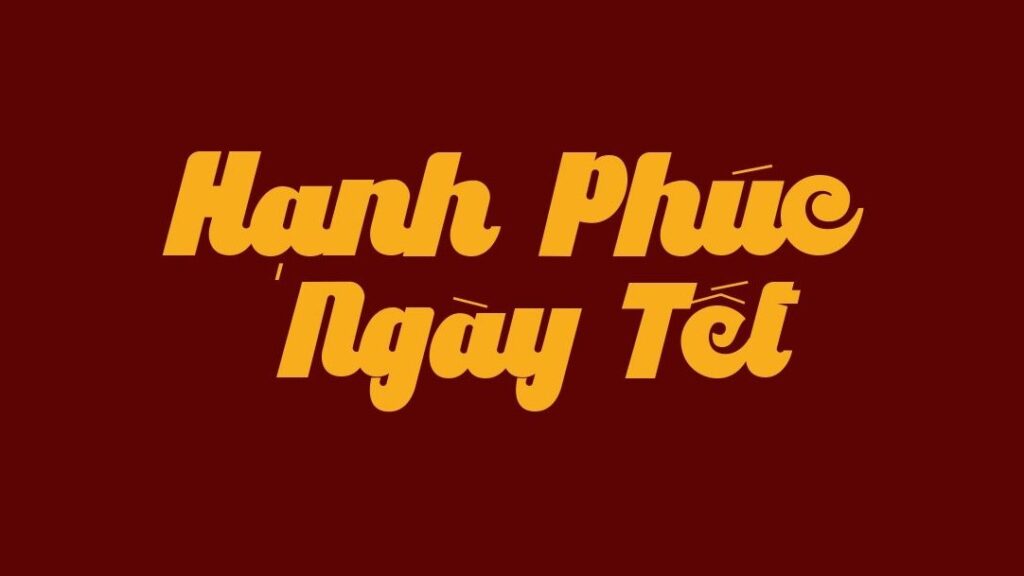
Font chữ Tết là nhóm phông chữ mang đậm âm hưởng lễ hội mùa xuân dân tộc, kết hợp tinh hoa giữa nét bút lông thư pháp truyền thống và tư duy đồ họa đương đại. Sở hữu các đường nét uốn lượn uyển chuyển, độ dày nét đậm đà và khí sắc hân hoan, font chữ Tết đẹp là chất liệu trực quan tuyệt vời để các kiến trúc sư, nhà thiết kế trang hoàng cho các bản vẽ phối cảnh cổng chào khu nghỉ dưỡng, ki-ốt bán hoa xuân container hay các ấn phẩm thiệp chúc mừng năm mới.
Khí sắc hân hoan mùa xuân và nét vẽ uyển chuyển của font chữ Tết
Điểm cuốn hút của font chữ Tết nằm ở nguồn năng lượng tích cực toát ra từ từng nét chữ, mô phỏng sinh động những câu đối đỏ của các ông đồ hay những vệt pháo hoa rực rỡ đêm giao thừa. Cấu trúc chữ sở hữu các đường lượn chữ thảo mềm mại, các góc nối nhịp nhàng mang lại nhịp điệu đọc tươi vui và ấm áp.
Sự ổn định về mặt cảm xúc của dòng font này giúp khơi gợi tình cảm sum vầy, sự may mắn và niềm hy vọng vào một khởi đầu hanh thông. Khi kết hợp cùng các vật liệu kiến trúc hiện đại xen lẫn truyền thống như vách panel sơn màu đỏ đô, khung thép uốn hoa văn, đèn lồng tre nứa hay cành mai, cành đào trong các căn nhà lắp ghép nghỉ dưỡng, phông chữ Tết tạo nên sự hòa quyện thẩm mỹ rực rỡ.
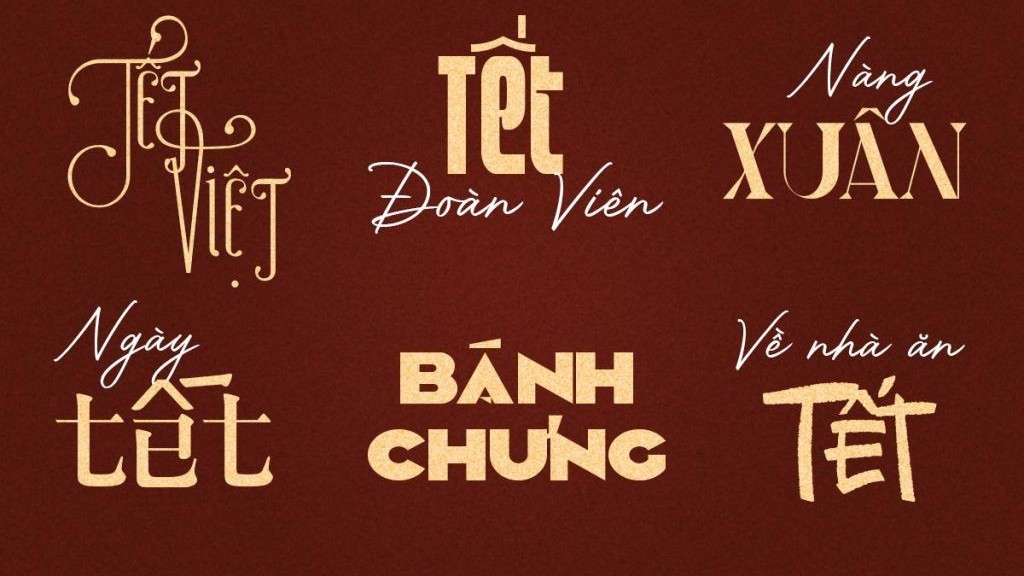
Tư vấn từ chuyên viên: Font chữ Tết sở hữu tính biểu tượng lễ hội rất cao. Để bản thiết kế đạt hiệu quả thẩm mỹ tốt, bạn nên sử dụng phông chữ này cho các tiêu đề chính, lời chúc đầu năm hoặc tên sự kiện. Phần nội dung mô tả kỹ thuật chi tiết nên đi kèm một phông chữ không chân thanh mảnh hơn để người xem tiếp nhận thông tin dễ dàng.
03 Ứng dụng phông chữ Tết vào không gian công trình thực tế
Nhờ vẻ ngoài rực rỡ và tính kết nối văn hóa mạnh mẽ, bộ phông chữ này mang lại giá trị thực tế lớn trong khâu trang hoàng cảnh quan đón năm mới:
- Hệ thống Cổng chào và Góc check-in Hội chợ Xuân: Những nét chữ thư pháp uốn lượn của phông chữ Tết rất ăn ý khi gia công chữ nổi bằng mica vàng gương hoặc cắt alu dán trên cổng chào tre nứa, tạo nên không khí tưng bừng và thu hút đông đảo người dân du xuân.
- Biển hiệu Ki-ốt kinh doanh quà Tết Container: Phông chữ này khi in trên bạt hiflex đỏ rực hoặc dán decal kính tại các gian hàng lưu động lắp ghép sẽ giúp cửa tiệm toát lên vẻ may mắn, kích thích nhu cầu mua sắm của khách hàng.
- Trang trí không gian sảnh đón tiếp Homestay và Văn phòng: Bạn có thể dùng phông chữ này để làm câu đối đỏ treo tường, bảng thông báo lịch nghỉ Tết hoặc thiệp mừng gửi đối tác, mang lại bầu không khí ấm cúng và sự gắn kết thân tình.
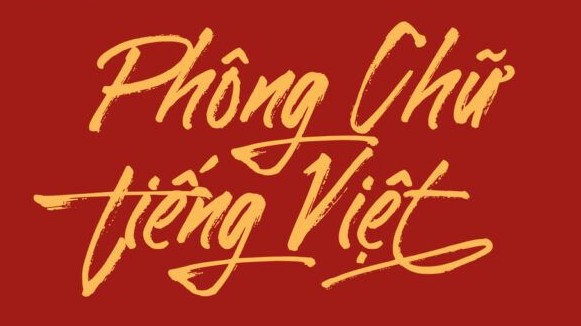
03 Lưu ý bố cục font chữ Tết hiện đại giữ trọn nét trang nhã
Để khai thác hiệu quả vẻ đẹp của dòng font lễ hội này mà không gây cảm giác lòe loẹt hay rối mắt, người thiết kế nên lưu tâm một số kinh nghiệm sau:
- Bố trí khoảng thở thoáng đãng: Do các ký tự thư pháp Tết thường có các nét đuôi vươn dài và uốn lượn, bạn nên chừa khoảng trống xung quanh tiêu đề rộng rãi để các nét cọ có không gian bay bổng, tránh để các cành hoa hay hoa văn phụ trợ chèn ép câu chữ.
- Tránh viết hoa toàn bộ ký tự: Các ký tự hoa của dòng phông này có cấu trúc nét rất phức tạp. Việc viết hoa liên tiếp nhiều chữ cái sẽ làm các nét móc va chạm nhau, gây mất bố cục và làm câu chúc trở nên khó đọc.
- Lựa chọn gam màu may mắn truyền thống: Phông chữ phát huy hiệu quả thị giác cao khi phối cùng các cặp màu kinh điển ngày Tết như đỏ son – vàng ánh kim, đỏ thắm – trắng kem hoặc xanh ngọc bích trên nền vàng đồng, làm nổi bật đường nét trang trọng của bộ chữ.